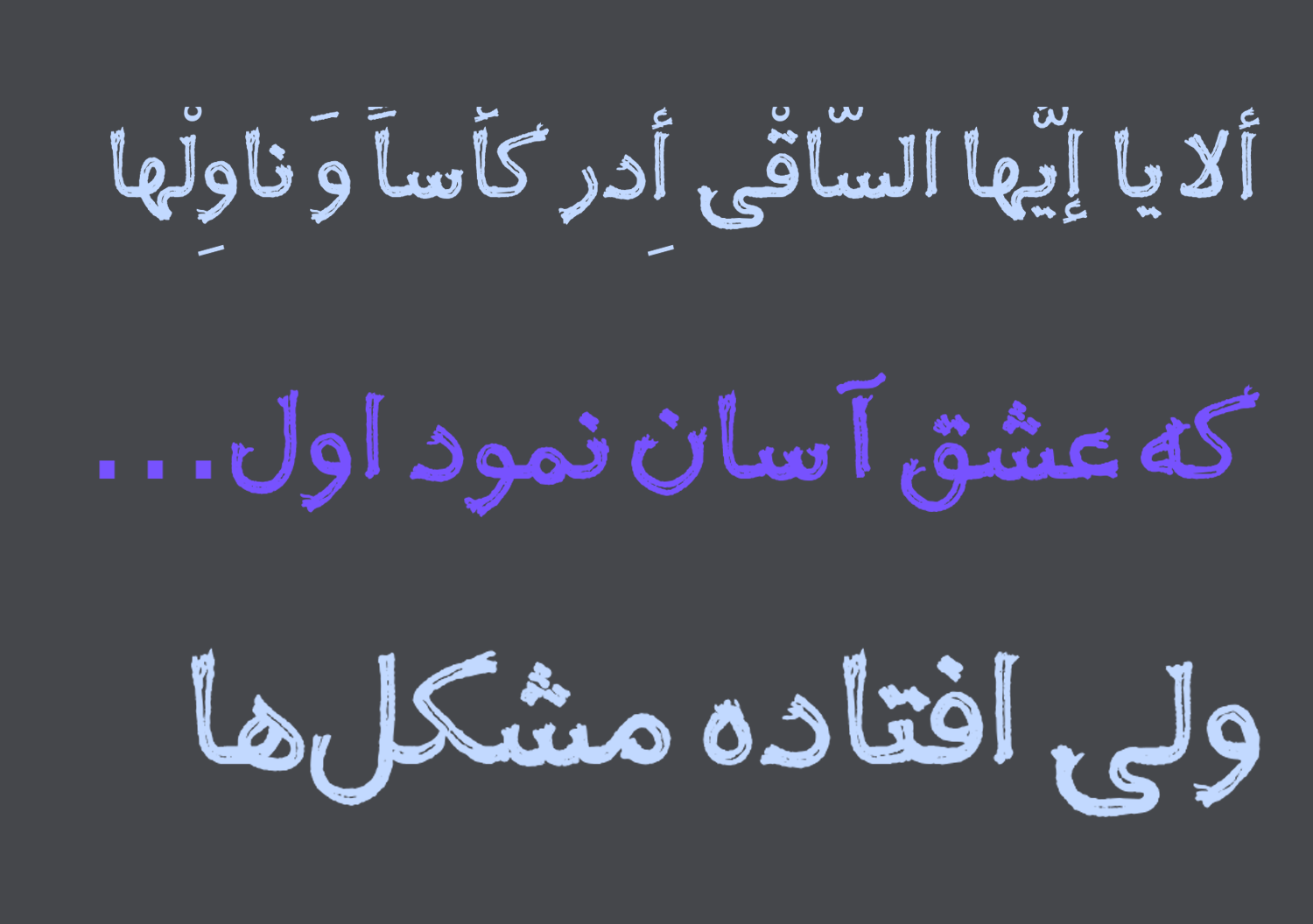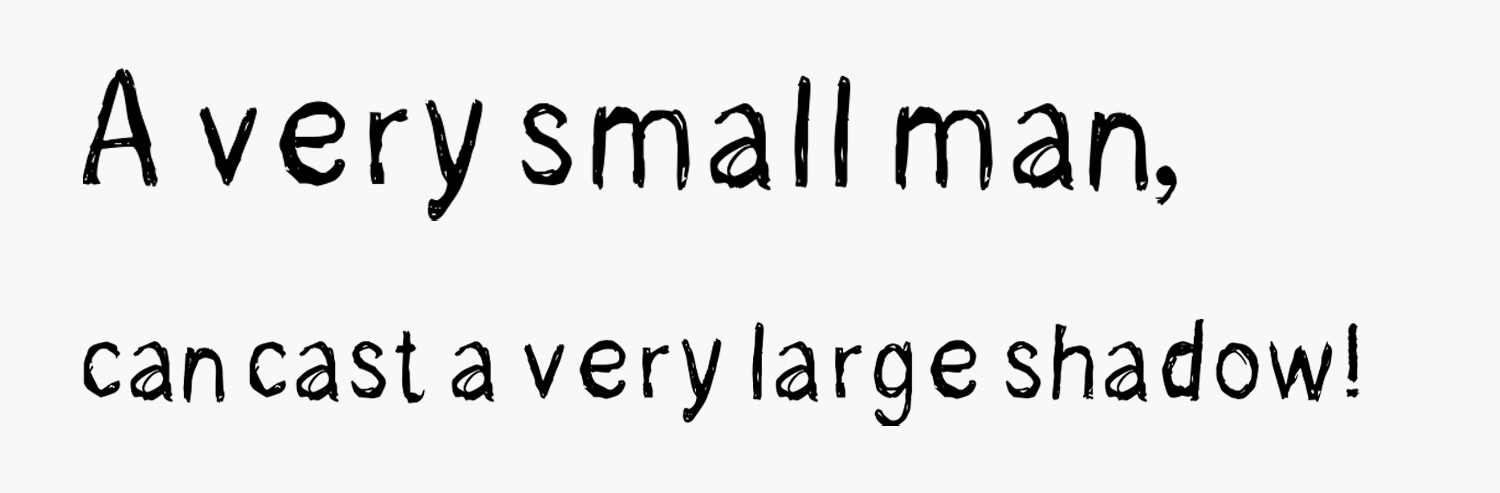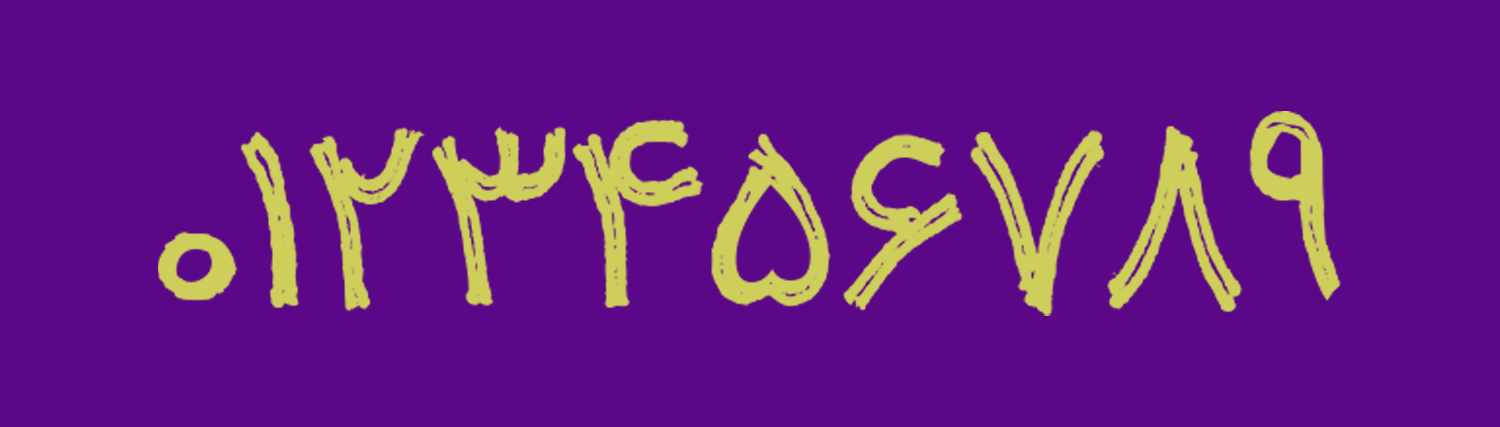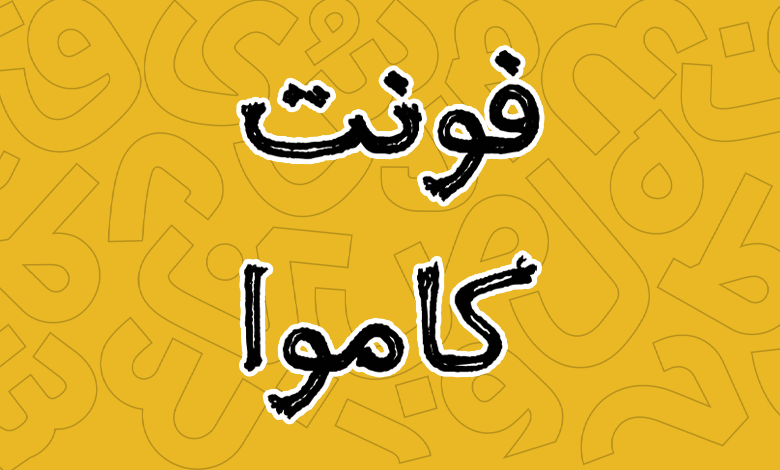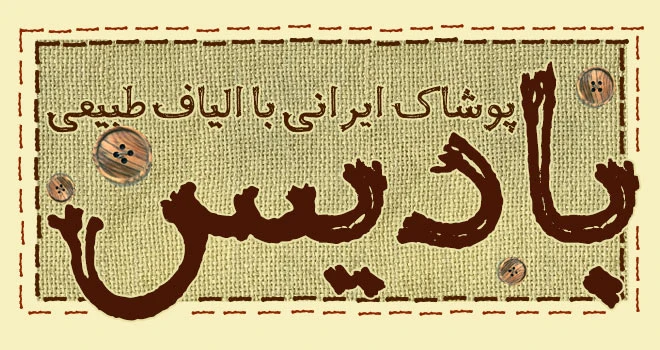
فونت کاموا (Kamva)
فونت کاموا (به انگلیسی: Kamva) در گروه قلم‌های فانتزی و نمایشی است که به صورت رایگان در دسترس قرار گرفته است. این قلم همانطور که از نامش مشخص است، از حروف‌چینی با استفاده از کاموا الهام گرفته شده است.
فونت رایگان کاموا توسط عطیه کامجو در قالب یک پروژه دانشجویی در کارگاه طراحی حروف مسلم ابراهیمی اجرا شده است که برای استفاده در ۳ زبان فارسی، عربی و انگلیسی مناسب است.
در ادامه این نوشته از سایت فونتچی به معرفی کامل این قلم پرداخته و ساختار و قابلیت‌هایی که این فونت برای هر یک از زبان‌های پشتیبانی شده را دارد مورد بررسی قرار خواهیم داد.
فونت کاموا رایگان است و برای استفاده از آن نیازی به پرداخت هزینه یا خرید لایسنس ندارید. این قلم دارای ساختاری فانتزی است که حروف در آن به اشکال مختلفی قرار گرفته‌اند. منحنی‌ها، دندانه‌ها، چشمی‌ها و سایر بخش‌های حروف که می‌توانند در برخی حروف و ترکیبات ساختاری یکسان در سایر فونت‌ها داشته باشند؛ در این قلم از این قائده تبعیت نمی‌کنند.
به طور کلی در این قلم سعی شده تا حروف زیاد پایبند به اصول و قواعد نباشد تا فونتی آزاد و نسبتا رها داشته باشیم. نقاط نیز در این قلم ساختاری جدا از هم دارند.
سبک طراحی و وزن فونت کاموا
حروف‌چینی فونت کاموا برگرفته از همان کاموا است. مشابه تصویر زیر می‌بینید که طراح با کنار هم قرار دادن دو بند کاموا سعی کرده تا حروف‌چینی این قلم را انجام دهد. دلیل استفاده از دو بند نیز این بوده است که در بخش‌های ابتدایی و انتهایی حروف، طره‌هایی که جنبه تزئینی داشته باشد ایجاد گردد.
در این قلم برای طراحی تمامی حروف سعی شده تا این طره ها طبق ساختاری که در ذهن طراح وجود داشته پیاده‌سازی شود تا فونت علاوه بر تزئینی بودن، یک ساختار هندسی و اینلاین هم داشته باشد. نظیر چنین قلم‌هایی را پیش از این در فونت گلچین، فونت ارژن و فونت سپید معرفی کرده‌ایم که یا تماما ساختار درون‌خطی دارند و یا اینکه یکی از وزن‌ها این ویژگی را دارد.
پشتیبانی از زبان عربی و انگلیسی
فونت فارسی کاموا محدود به این زبان نبوده و با توجه به رسم‌خط یکسانی که در بیشتر زبان‌های خاورمیانه‌ای وجود دارد، از این قلم می‌توانید برای زبان عربی و برخی دیگر از زبان‌های کردی و اردو نیز استفاده کنید. هر چند که زبان عربی نسبت به سایر زبان‌ها پشتیبانی کامل‌تری را دارد. در حالی که سایر زبان‌ها فاقد گلیف‌های تزئینی یا ساختار متفاوت حروفی مثل «ﮧ، ﮩ، ے» در اردو هستند.
در تمامی حروف فارسی و عربی که به صورت مشترک هستند ساختار یکپارچه حفظ شده است؛ اما در برخی جاها کاستی وجود دارد که روی آنها کار نشده است. برای مثال در زبان عربی که حروفی مثل «ک، ی، ه، ؤ، ئ» که ساختاری متفاوت نسبت به فارسی از نظر قرارگیری نقاط یا همزه دارند کار نشده است.
این قلم همچنین از زبان انگلیسی با همان ساختار نسبتا خطی هاشور خورده پشتیبانی می‌کند که در تمامی حروف سعی شده حفظ شوند. اما یک تفاوت عمده‌ای که نسبت به نسخه فارسی دارد در این است که طره‌های تزئینی در ابتدا و انتهای حروف برای زبان انگلیسی وجود ندارد.
پشتیبانی از اعداد فارسی
این قلم اساسا برای زبان فارسی طراحی شده است و اگر اینکه می‌گوییم برای زبان عربی، کردی و اردو هم قابل استفاده است؛ صرفا در شرایط است که بخواهید از رسم خط فارسی در این زبان‌ها استفاده کنید. همین مسئله باعث شده تا قلم برای سایر زبان‌ها در بخش اعداد یک کاستی دیگر داشته باشد.
برای زبان فارسی تمامی اعداد فارسی پشتیبانی می‌شوند. اما در زبان عربی که اعداد «۴۵۶» تایپ متفاوتی نسبت به فارسی دارند، وجود ندارد.
مناسب کارهای تزئینی و فانتزی
از فونت کاموا رایگان می‌توانید در انواع کارهایی که جنبه گرافیکی، تزئینی و فانتزی دارند استفاده کنید. با توجه به اینکه قلم بر اساس کنار هم‌قرارگیری و حروف‌چینی کاموا ساخته شده است، می‌تواند استفاده موثری در صنعت پوشاک و پارچه داشته باشد که در تصویر زیر نمونه‌ای از آن را می‌بینید.
اما در موارد دیگری همچون چاپ کاتالوگ، تبلیغات، کتاب کودک و نوجوان و دیگر موارد هم می‌توانید از این قلم رایگان استفاده کنید.